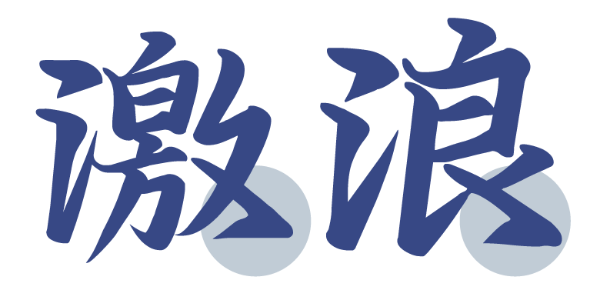
一款激情澎湃的手写字体
书写字体
汉仪小松激浪体是由汉仪签约作者孙小松创作的一款激情澎湃的手写字体,风格潇洒个性、自由奔放,洋溢着青春的气息。抑扬顿挫的手写带来的节奏感以及率性的连笔带来的流畅感,使得这款字体蓄有前进的动势。这款字体适合用于标题文本或较短文本的排版,在运动等需要体现青春热血的使用场景中烘托热情的氛围并彰显个性。
抑扬顿挫的手写带来节奏感,率性的连笔带来流畅感,整体蓄有动势。
捺笔收笔处的回勾就像是激起层层浪花,向着常规的阅读排版方向前进,激情澎湃,充满活力。
这款字体的西文部分同样以饱满的热情进行书写,笔画饱满而富有张力。